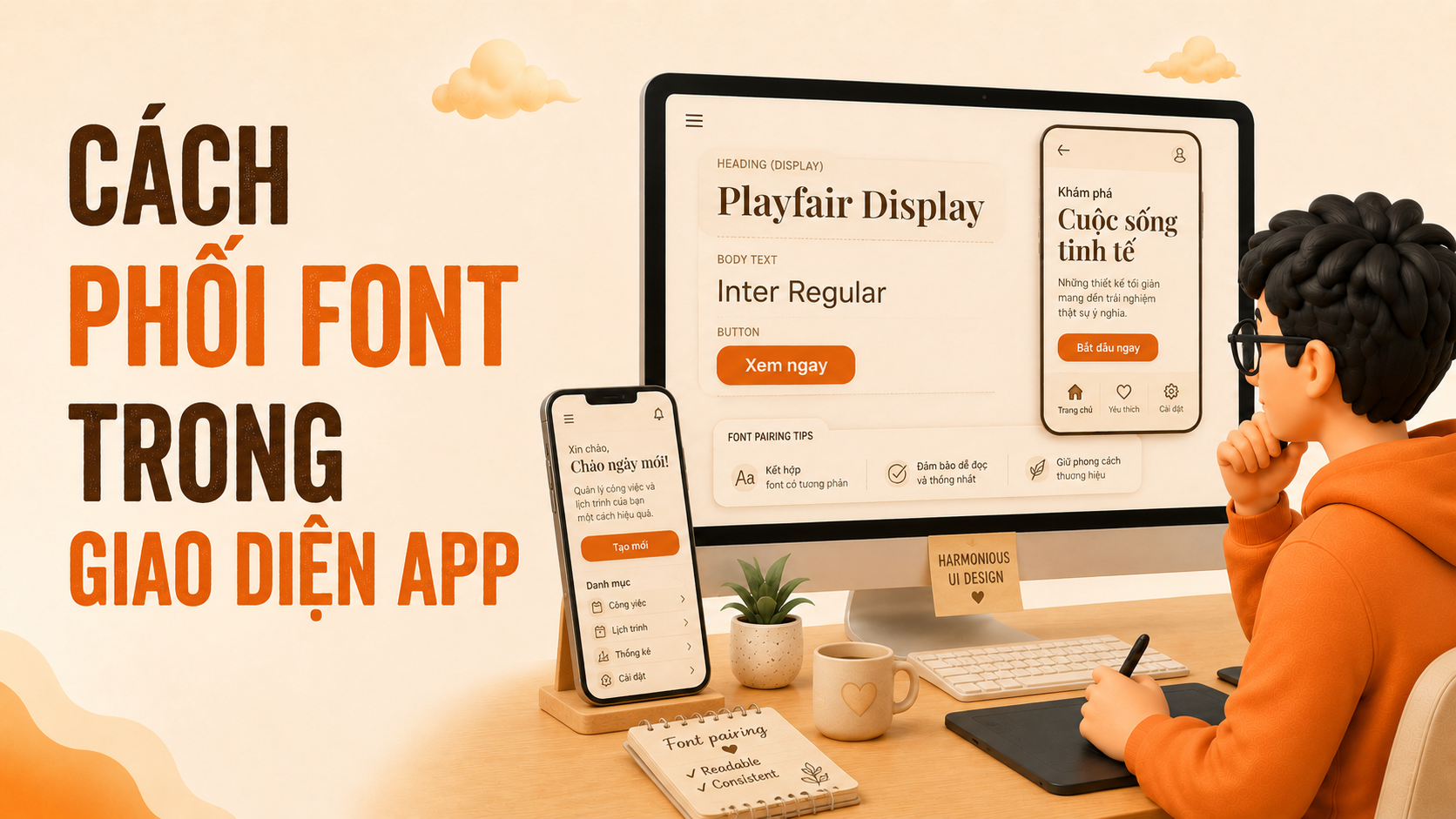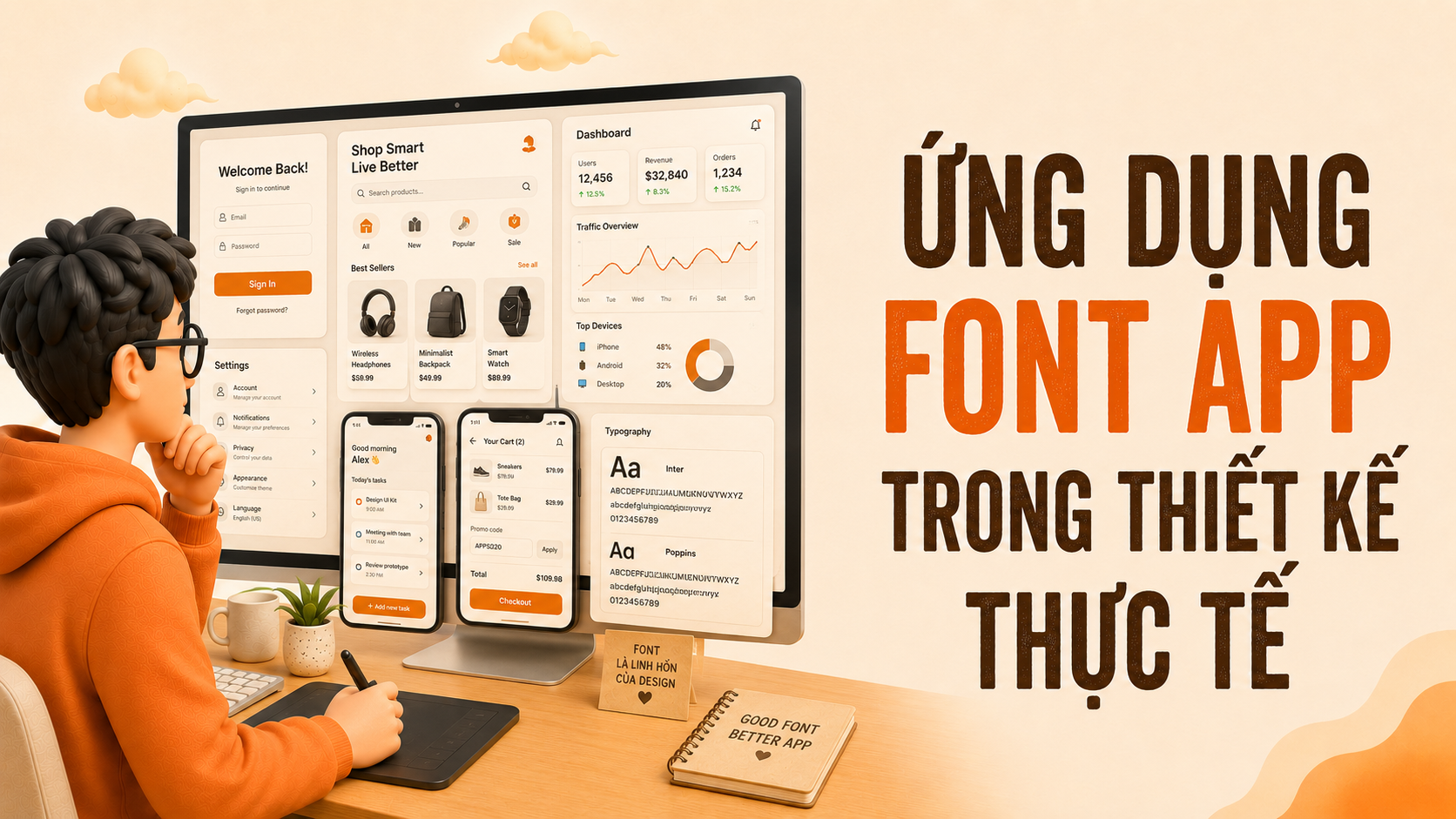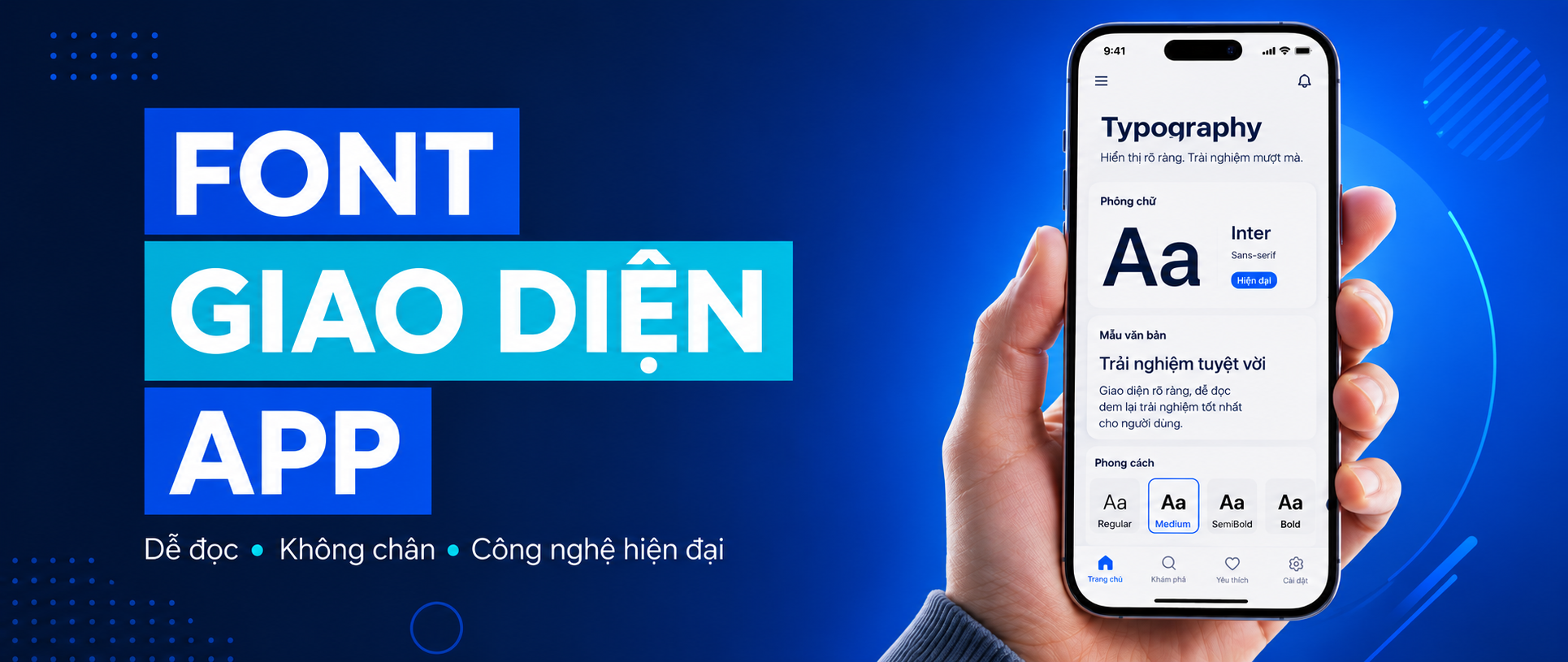
Giao diện app cần một loại chữ rất khác poster hay logo. Người dùng không chỉ nhìn cho đẹp; họ cần đọc nhanh, bấm đúng, hiểu trạng thái, nhận ra lỗi, so sánh giá, nhập thông tin và hoàn thành thao tác trong vài giây. Vì vậy, font chữ giao diện app phải rõ ràng, ổn định, hỗ trợ tiếng Việt tốt và dùng được ở nhiều kích thước.
Trong UI app, font là một phần của trải nghiệm người dùng. Một nút “Tiếp tục” phải đọc được ngay. Một thông báo lỗi phải rõ. Một con số trong ví điện tử phải không gây nhầm. Một dòng mô tả dịch vụ phải đủ thoáng để người dùng không bỏ qua.
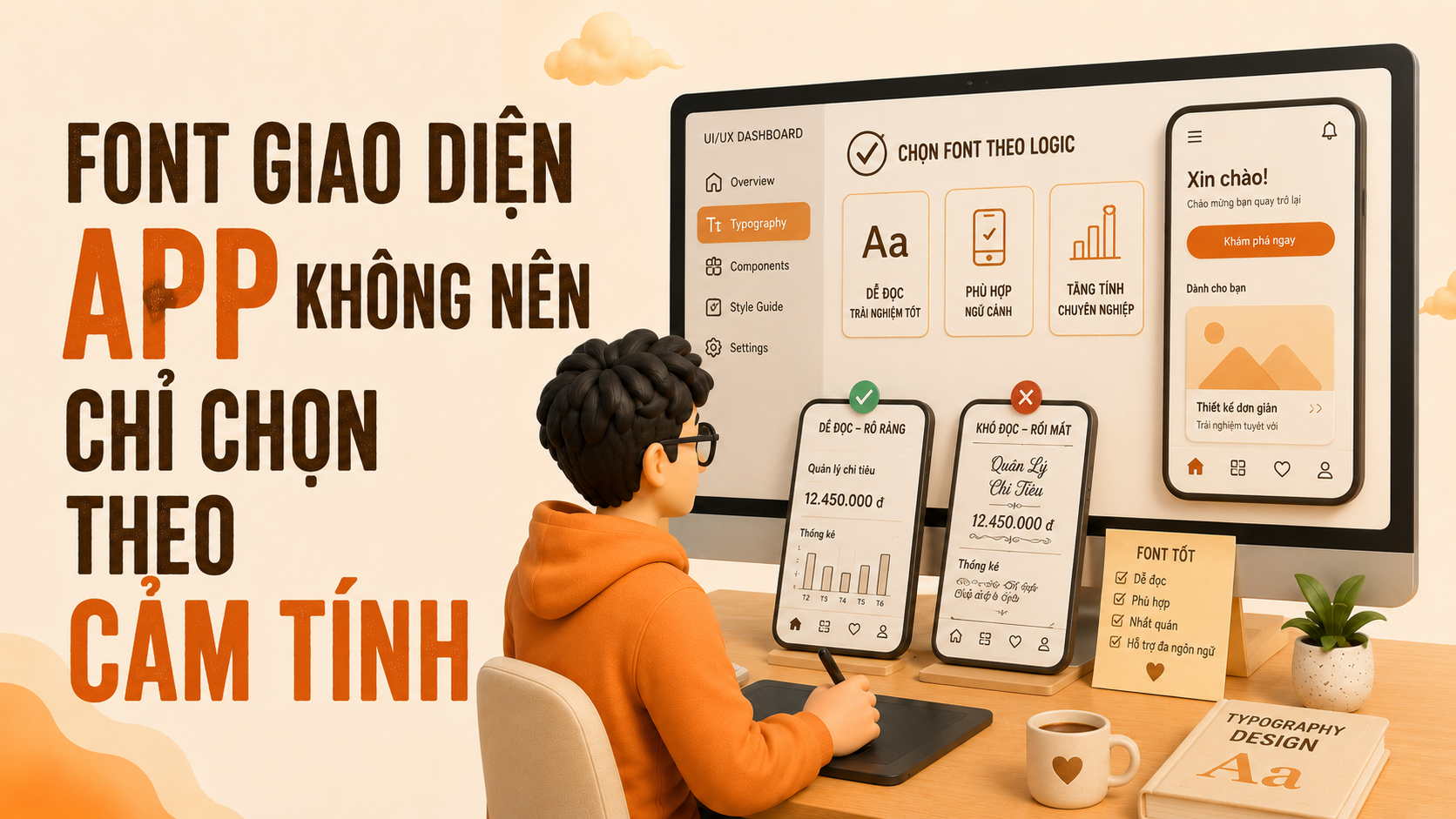
Nếu font quá mảnh, app nhìn đẹp ở màn hình mockup nhưng khó đọc trên điện thoại cũ. Nếu font quá cá tính, giao diện có thể mất sự tin cậy. Nếu dấu tiếng Việt lệch, các cụm như “Đăng nhập”, “Thanh toán”, “Lịch hẹn”, “Đặt bàn”, “Tài khoản”, “Ưu đãi” sẽ nhìn thiếu chuyên nghiệp.
Với giao diện app, designer nên ưu tiên font có nét sạch, x-height tốt, khoảng cách chữ cân bằng, hỗ trợ tiếng Việt đầy đủ và có nhiều độ đậm nếu có thể. Font chính không cần quá nổi bật; nó cần giúp người dùng hoàn thành việc của họ.
App có rất nhiều chữ nhỏ: label, placeholder, caption, helper text, trạng thái, thời gian, ghi chú, badge và navigation. Font cần giữ được độ rõ ở các cỡ 11-14px, đặc biệt trên màn hình có độ sáng thấp.
Tiếng Việt trong app có nhiều dấu đặt ở phía trên và dưới chữ. Font Việt hóa tốt giúp giao diện sạch hơn, nhất là trong các dòng ngắn như “Quên mật khẩu?”, “Đã thanh toán”, “Đang giao hàng”, “Cập nhật hồ sơ”.
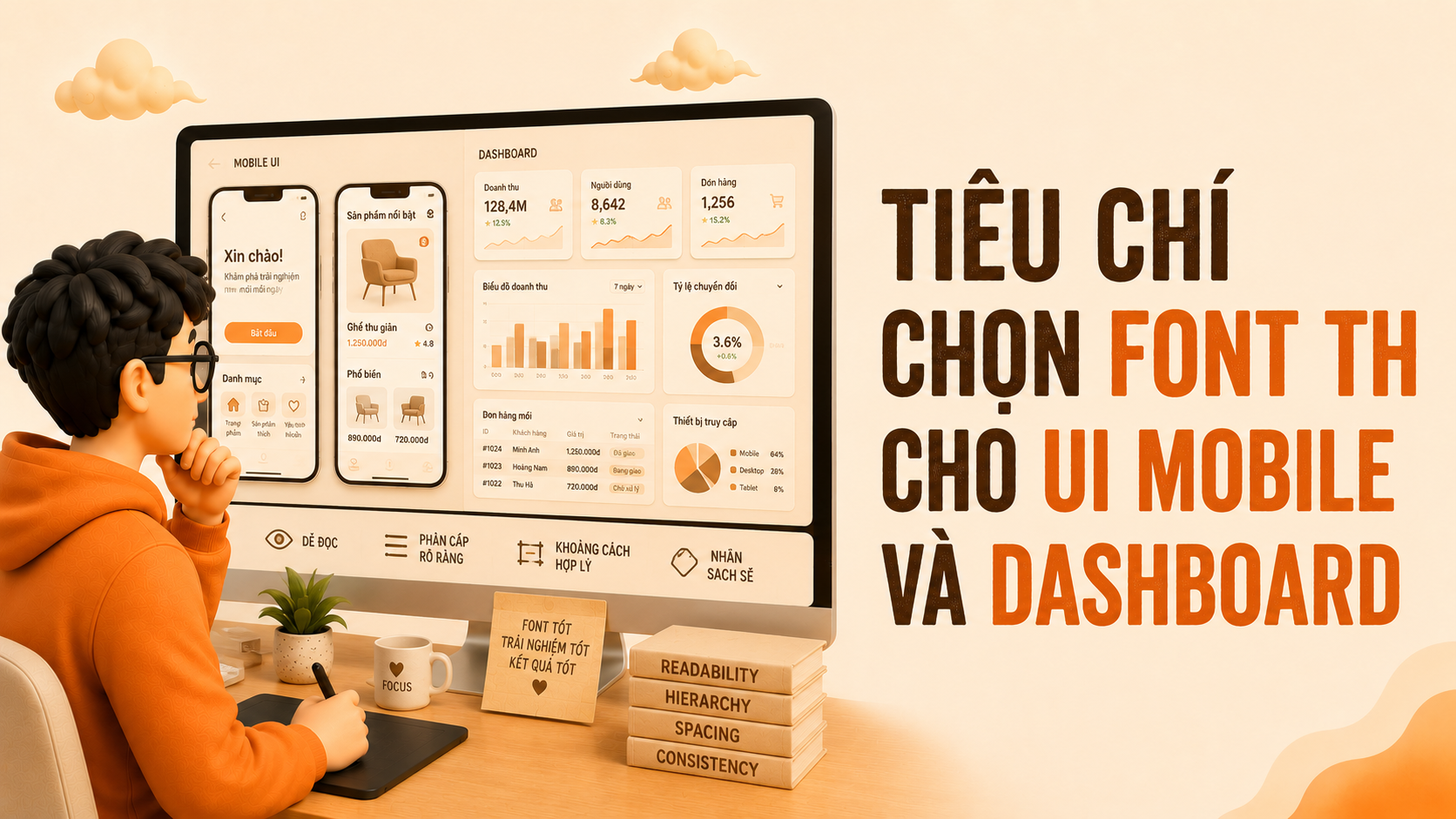
Một UI thường cần regular cho nội dung, medium cho label, semibold hoặc bold cho heading, button và số liệu quan trọng. Nếu font chỉ có một kiểu, designer sẽ khó tạo hierarchy nhất quán.
Font app nên đủ trung tính để dùng lâu dài, nhưng vẫn cần hợp ngành. Fintech cần chắc và tin cậy. Health app cần sạch và dịu. Food app có thể bo tròn hơn. App công nghệ cần hiện đại, gọn và có cảm giác logic.
Một font UI tốt nên dùng được cả trong landing page, email, push notification, banner app store, social post và presentation sản phẩm. Sự nhất quán giúp thương hiệu app nhìn chuyên nghiệp hơn.
Nhóm này phù hợp làm font nền cho toàn bộ app: menu, body text, form, card, tab, bảng giá, thông báo, profile và các màn hình có nhiều nội dung. Đây là nhóm nên thử đầu tiên nếu bạn đang làm app thật.
Những font này hợp với app dịch vụ, quản lý công việc, học tập, đặt lịch, thương mại điện tử, app nội bộ và dashboard. Khi dùng, hãy đặt line-height thoáng, tránh chữ quá sát mép card và kiểm tra kỹ các trạng thái lỗi/cảnh báo.
Nếu app thuộc nhóm công nghệ, AI, tài chính, blockchain, SaaS, dashboard dữ liệu hoặc sản phẩm B2B, font nên có cảm giác logic, hiện đại và chắc. Nhóm dưới đây phù hợp cho heading, hero section, metric card và màn hình onboarding.
Nhóm này nên dùng có kiểm soát. Một số font mạnh rất hợp headline, nhưng chưa chắc phù hợp cho toàn bộ body text. Với app tài chính, hãy kiểm tra kỹ số tiền, phần trăm, mã giao dịch và bảng dữ liệu.
Không phải app nào cũng cần cảm giác công nghệ. App chăm sóc sức khỏe, đặt lịch clinic, giáo dục, mẹ và bé, wellness, beauty booking hoặc community app thường cần font mềm hơn, thân thiện hơn nhưng vẫn sạch.
Font TH Cameo Sans - Tải về
Font TH Luxury 8 - Tải về
Font TH Runalto - Tải về
Font TH Selaris - Tải về
Font TH Leky Calgria - Tải về
Nhóm này hợp với app làm đẹp, app đặt lịch spa, app clinic, app sức khỏe tinh thần, khóa học online và thương hiệu cá nhân. Nên dùng cho heading, màn hình giới thiệu hoặc section cao cấp; phần form và nội dung dài vẫn nên dùng font rõ hơn.
App đồ ăn, trà sữa, bán hàng trẻ trung, loyalty app, app trẻ em hoặc cộng đồng có thể cần font bo tròn hơn. Font bo tròn giúp giao diện thân thiện, vui và dễ gần, nhưng không nên dùng quá nhiều nếu app cần xử lý thông tin phức tạp.
Font TH Bagyo Sans - Tải về
Font TH Yorkmade - Tải về
Font TH Choco Fantine - Tải về
Font TH Mighty Kingdom - Tải về
Nhóm này chỉ nên dùng cho heading, empty state, banner ưu đãi, sticker “new”, onboarding vui hoặc section điểm thưởng. Không nên dùng cho bảng giá dài, điều khoản, lịch sử đơn hàng hoặc nội dung cần độ chính xác cao.
Font chữ giao diện app cần rõ, ổn định, hỗ trợ tiếng Việt tốt và phù hợp hành vi người dùng. Nếu muốn an toàn, hãy bắt đầu với nhóm sans-serif TH sạch. Nếu cần cá tính công nghệ, dùng font TH hiện đại cho heading. Nếu app thiên lifestyle, clinic hoặc F&B, chọn font mềm hoặc bo tròn nhưng vẫn giữ phần nội dung chính thật dễ đọc.